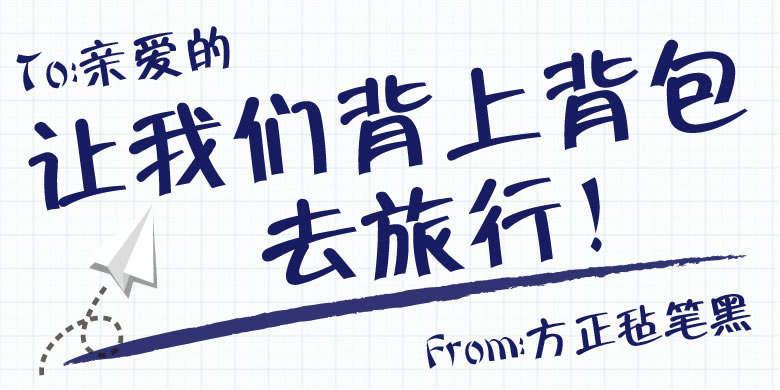
方正毡笔黑繁体
品牌:方正字库设计师:倪初万发行时间:2003字库编码:大陆简体(GB2312-80)、大陆繁体(GB12345-90)、简繁扩展(GBK)、港台地区(BIG-5)分类:创意字体
方正毡笔黑繁体
方正毡笔黑是一款具有POP风格的创意手写字体。这款字体的笔画形态是对毡头笔书写特点的几何概括,起笔处呈圆形,横笔画左粗右细,字形结构整体右上倾斜,富有动感。方正毡笔黑的风格干净利落,易读性强,尤其适用于时效性的广告设计,以及儿童类品牌的产品包装设计。